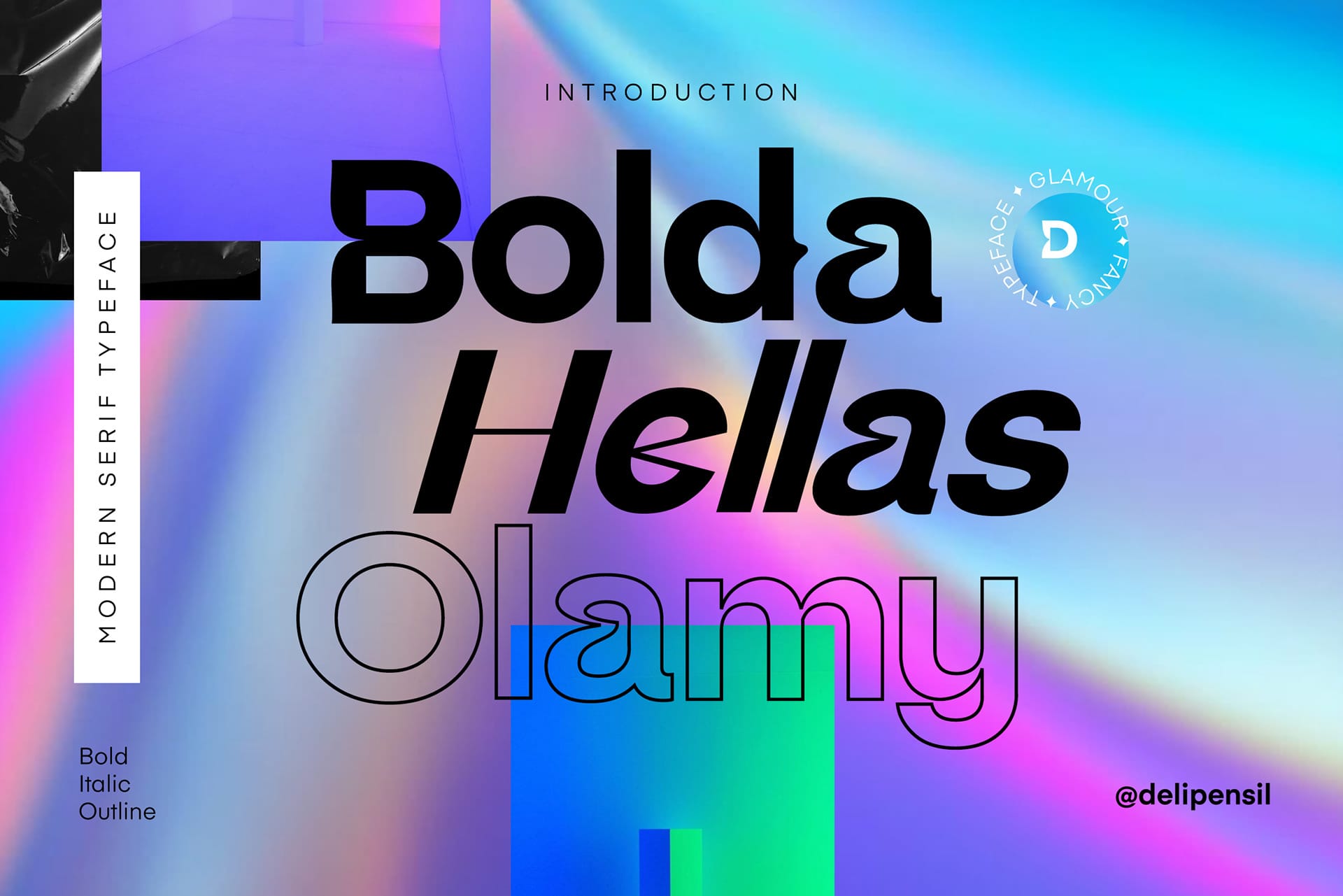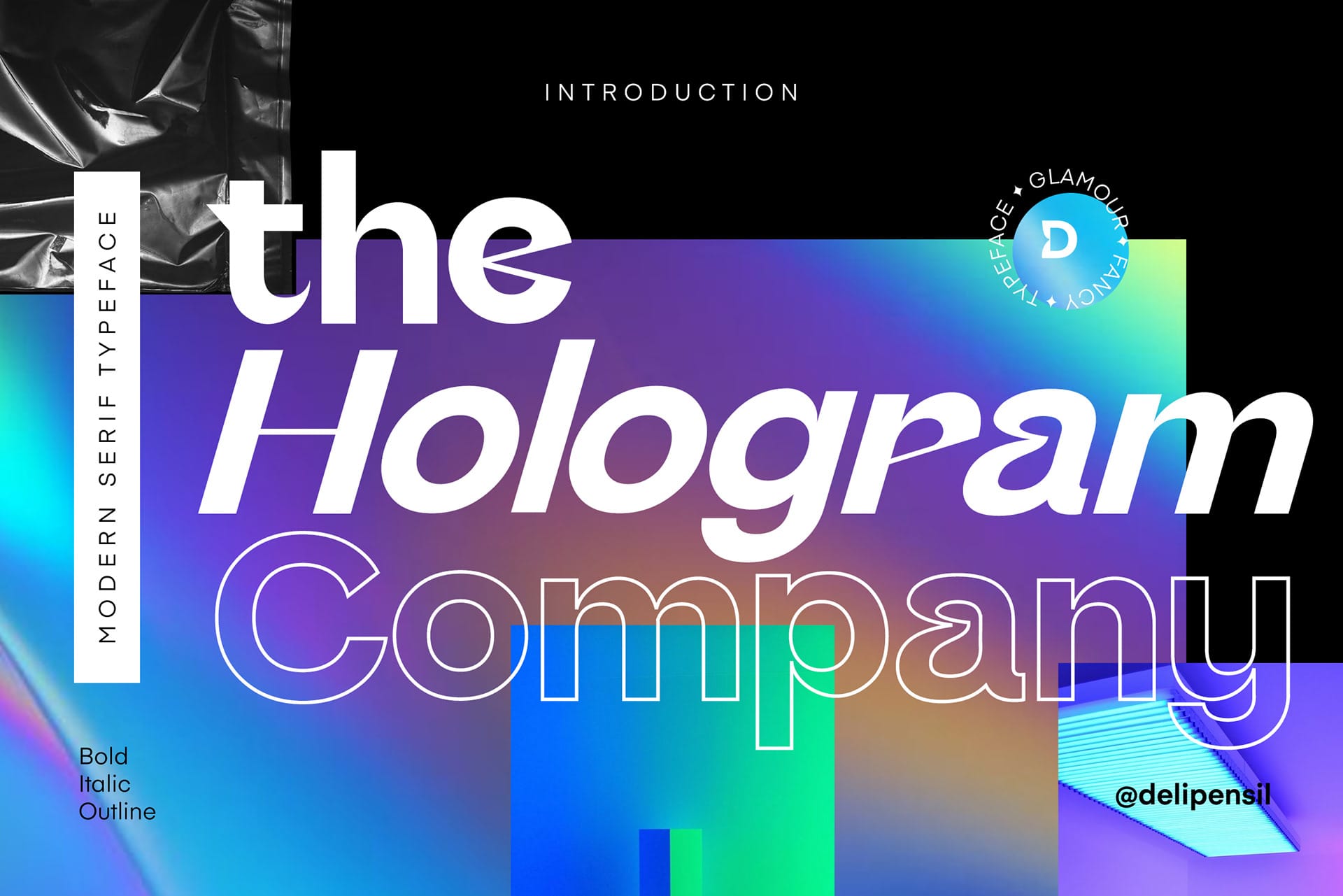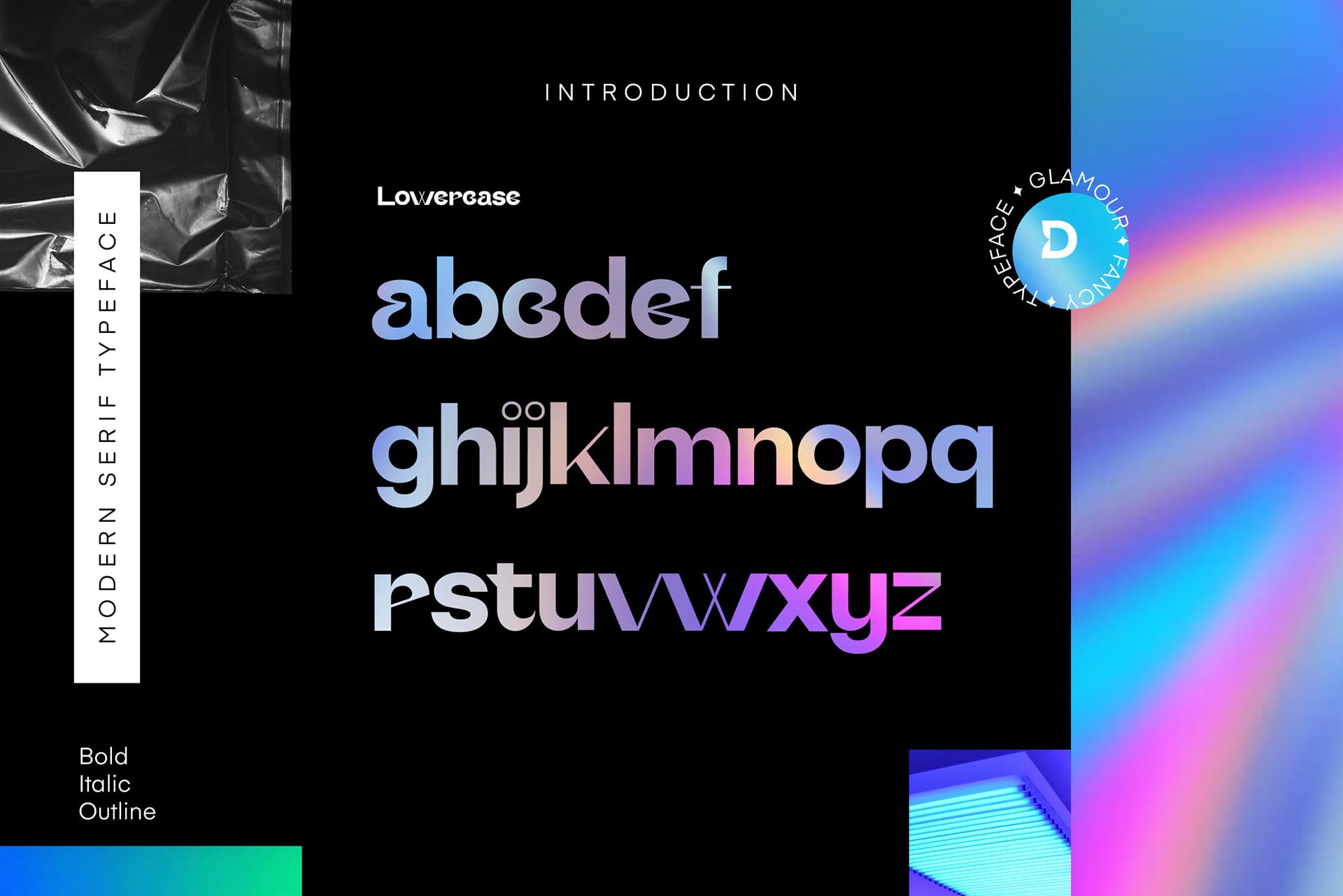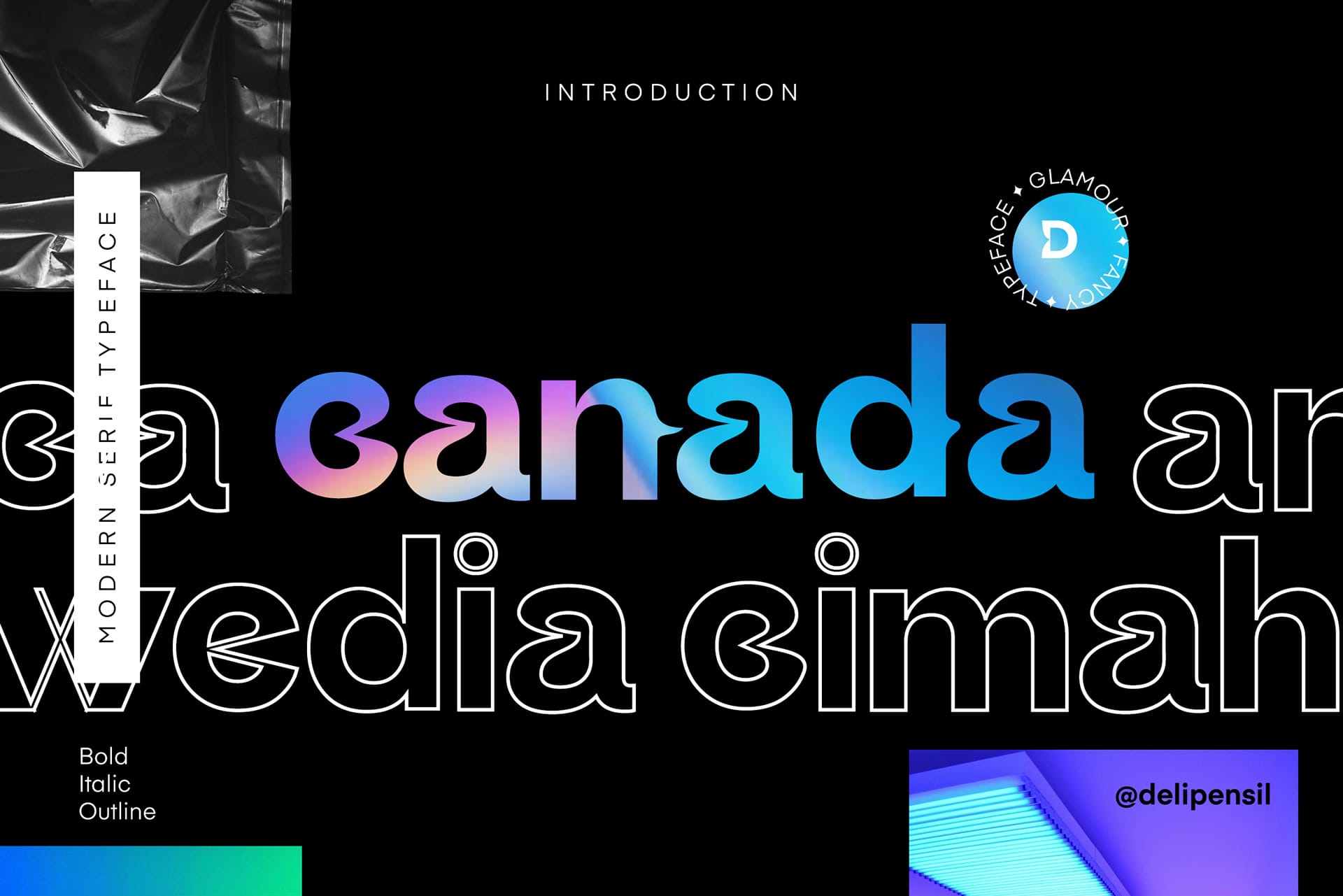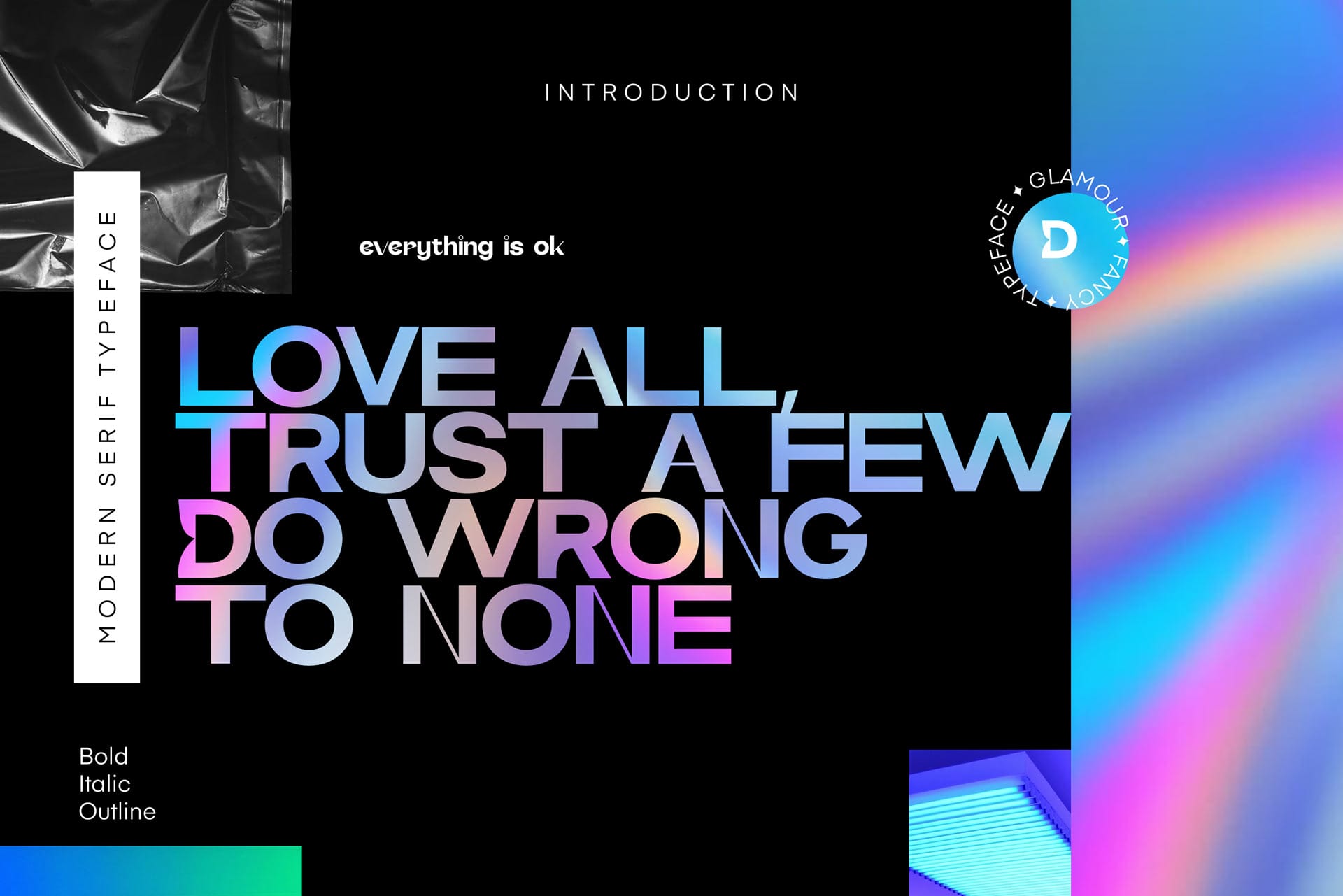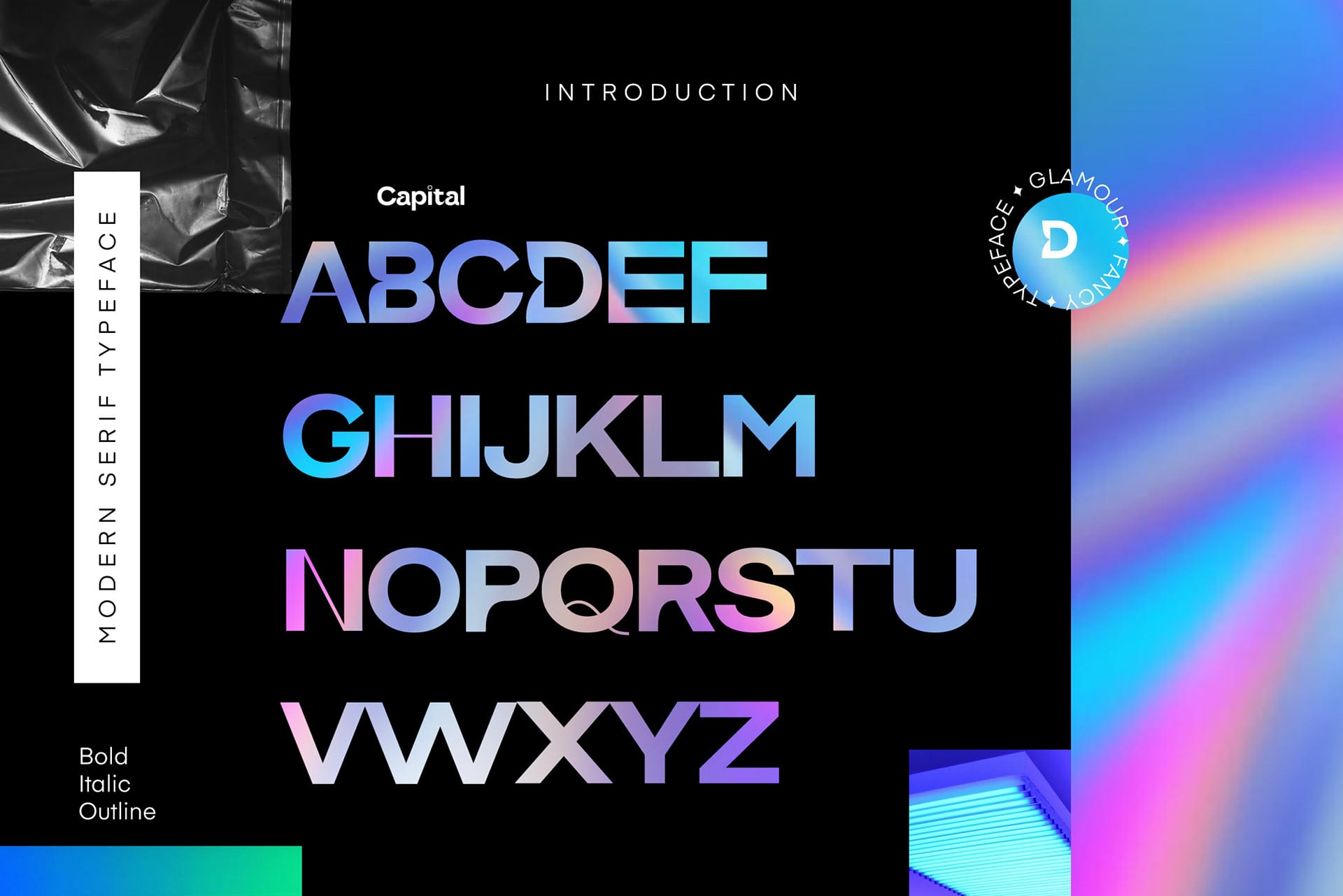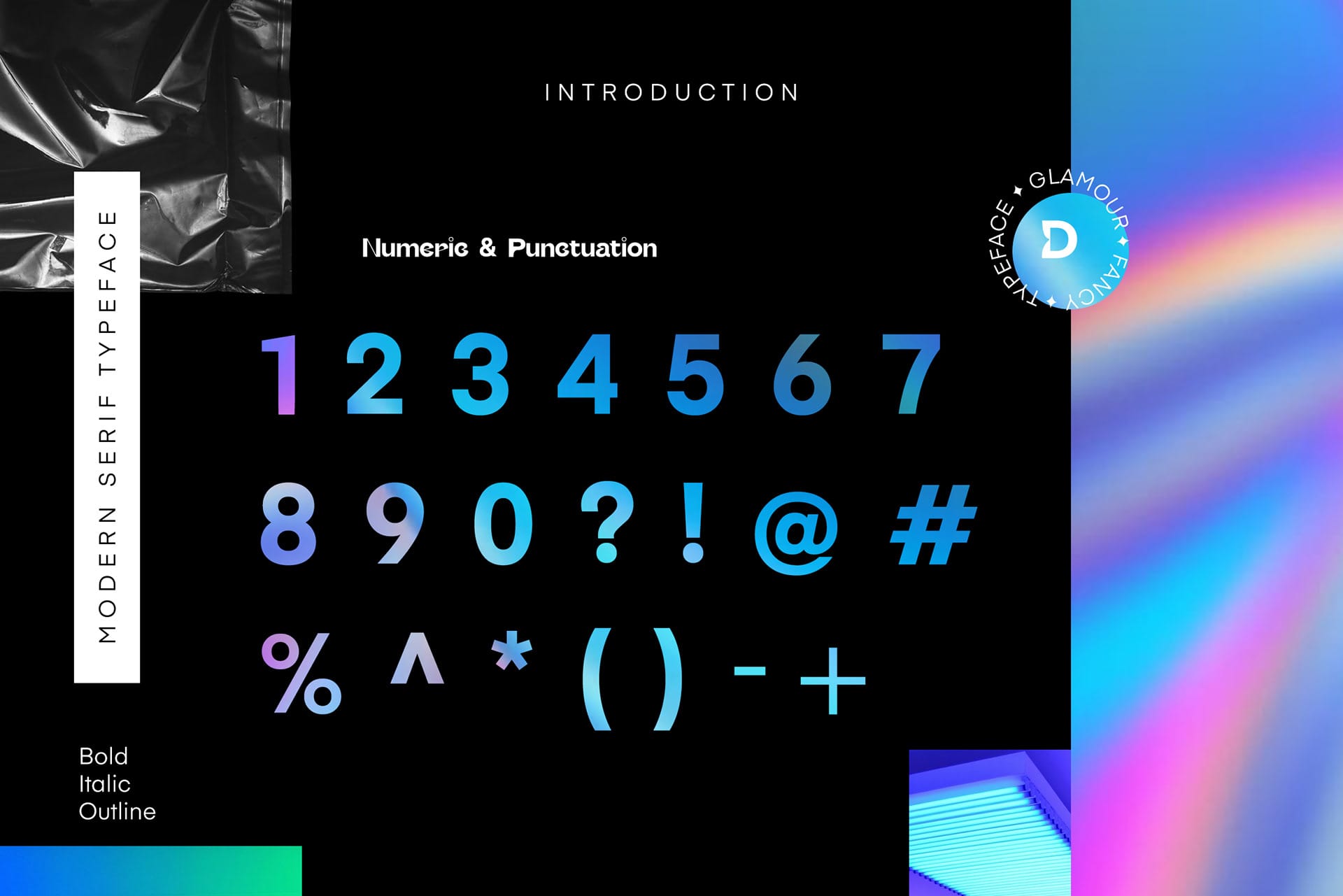
Giới thiệu Font Coldag Modern – Kiểu chữ Serif hiện đại 👑✨
Font chữ Coldag Modern Serif với thiết kế thanh lịch, đẹp và hiện đại, kết hợp phông chữ này với phong cách của bạn, sử dụng font chữ này cho bất kỳ thiết kế nào cho logo, tiêu đề, sách bìa, tạp chí của bạn và nhiều hơn nữa.
• Coldag – 3 Font Type [Bold, Italic, Outline]
• Coldag – Kerning Style
• Coldag – Modern Feel